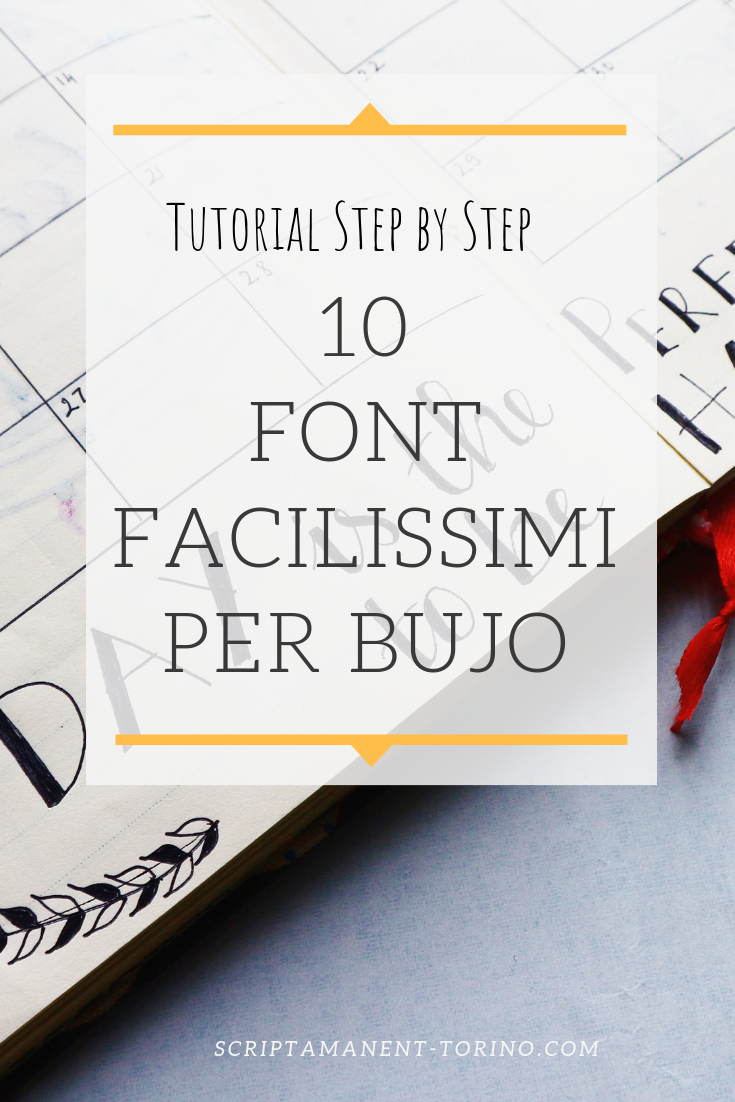
Font Scrittura A Mano Titoli
Fibre è un font moderno in stile scrittura a mano Tutti i caratteri sono di base diversi tra loro Le metriche e le creste di questo carattere in stile vintage sono state sviluppate per una certa facilità di lettura che solo un font interamente in maiuscolo può offrire HUMBLLE ROUGHT.
Font scrittura a mano titoli. Handwritten Font Bundle by Ian Barnard Ottieni un aspetto in stile “scrittura a mano” con questi font essenziali In questo fantastico pacchetto sono inclusi cinque font Bloomsbury Un carattere disegnato a mano in tre stili, Script, San e Serif, realizzati in modo da poterli utilizzare in combinazione tra loro. 10apr Esplora la bacheca "Calligrafia titoli" di Antonella su Visualizza altre idee su font di scrittura, idee per diario, scrittura a mano. 30giu Esplora la bacheca "Scritte per titoli e appunti" di Azzurra Genovese su Visualizza altre idee su scrittura a mano, font di scrittura, alfabeto scritto a mano.
Un font corsivo scritto a mano di solito non è davvero scritto a mano, è solo progettato per apparire come esso è Font in questo stile includono scolastico, Snell Roundhand e Santa Fe Molti font con la parola "script" nei loro nomi sono i caratteri della scrittura a mano di ispirazione corsivo, come Edwardian Script, Script e Bickham Brush. Tutte le 100% gratuiti base Sans Serif Serif Slab Serif manoscritto decorativo Dingbats non latino Pixel stile 3D squadrato cartoni carino arricciato futuristico Grunge bordo a mano pennellato corsivo calligrafia graffiti scrittura a mano schizzato graffiato stencil storico art deco art nouveau scrittura gotica medievale Retro macchina. L'app Font Changer ha la più grande raccolta di caratteri sul Play Store Crea i tuoi messaggi più interessanti, aggiornamenti di Facebook, Instagram Bio o tweet con oltre 110 caratteri speciali!.
26mar Esplora la bacheca "Scritture" di Sofia Mary su Visualizza altre idee su Scrittura a mano, Scrittura, Calligrafia. Imitano la scrittura a mano e anche questi sono font perfetti per un sito professionale, almeno per i titoli, perché conferiscono eleganza e stile alla pagina Un esempio di utilizzo di un font calligrafico Font gotici. Tutte le 100% gratuiti base Sans Serif Serif Slab Serif manoscritto decorativo Dingbats non latino Pixel stile 3D squadrato cartoni carino arricciato futuristico Grunge bordo a mano pennellato corsivo calligrafia graffiti scrittura a mano schizzato graffiato stencil storico art deco art nouveau scrittura gotica medievale Retro macchina.
7apr Esplora la bacheca "lettering" di Elisa Vanzani su Visualizza altre idee su Idee per diario, Font di scrittura, Idee per appuntamenti. Sono originali e intramontabili i font calligrafici sono perfetti per i tuoi progetti grafici, specialmente se hai l’esigenza di una tipografia sofisticata o ricercata Sul web sono disponibili centinaia di font, free e non in questo articolo ho voluto selezionare per te i 25 font calligrafici che reputo migliori e capaci di dare ai tuoi lavori quel tocco che può fare la differenza. Font di Scrittura a Mano La scrittura a mano può essere un concetto molto distante per tante persone nell’odierno mondo digitalizzato, grazie ai vari dispositivi elettronici, e non è strano che nella maggior parte dei casi incontriamo i noiosi Times New Roman o Verdana, anche se riceviamo un biglietto d’auguri.
Progettato prendendo ispirazione dalle insegne delle lavanderie di San Francisco, questo font è perfetto per i titoli e per tutti quei progetti in cui si vuol ottenere un effetto vintage DOWNLOAD 5 Monthoers è un font che simula le caratteristiche delle lettere stampate a mano. Imitano la scrittura a mano e anche questi sono font perfetti per un sito professionale, almeno per i titoli, perché conferiscono eleganza e stile alla pagina Un esempio di utilizzo di un font calligrafico Font gotici. Tutte le 100% gratuiti base Sans Serif Serif Slab Serif manoscritto decorativo Dingbats non latino Pixel stile 3D squadrato cartoni carino arricciato futuristico Grunge bordo a mano pennellato corsivo calligrafia graffiti scrittura a mano schizzato graffiato stencil storico art deco art nouveau scrittura gotica medievale Retro macchina.
10apr Esplora la bacheca "Calligrafia titoli" di Antonella su Visualizza altre idee su font di scrittura, idee per diario, scrittura a mano. I migliori convertitori di testo per convertire testo noioso in testo divertente!. Un generatore di font e uno switcher di s crittura per il copia e incolla diretto Converte il testo in testo semplice in vari stili di font come i font per tatuaggi, i font per la scrittura a mano, i font per script web, i font corsivi, i font scritti a mano, i vecchi font inglesi, le lettere, i bellissimi font o i font artistici.
Caratteri dei quali con accenti con il simbolo dell'Euro. Il nostro obiettivo è quello di realizzare l’effetto scrittura a mano utilizzando il pennello dell’effetto Scrivi sopraIl parametro da animare sarà pertanto la posizione del pennello Posizioniamo il pennello immediatamente sotto la prima R di River Quindi regoliamo la dimensione del pennello in modo da coprire interamente col diametro lo spessore del carattere. Adriana à € di Kong Font scaricati (6874 ieri) Shareware 4 file dei caratteri Scarica Dona all'autore Hello di Graphix Line Studio scaricati (6336 ieri) 21 commenti Gratis per uso personale 2 file dei caratteri Scarica Dona all'autore.
21ott Esplora la bacheca "Calligrafia" di Angela Pezzoli su Visualizza altre idee su calligrafia, scrittura a mano, scrittura. Quindi il font, in tipografia e informatica, è un insieme di caratteri per la stampa (stampatello è la scrittura a mano che richiama, con le lettere staccate, il carattere usato per la stampa) e per la lettura a monitor (carattere digitale, font installabile sulle nostre macchine e utilizzabile per la composizione). 14ago Esplora la bacheca "font di scrittura" di Cristianaoguguanebo su Visualizza altre idee su Font di scrittura, Scrittura, Idee per diario.
Anche se non è scritto a mano, imita la scrittura corsiva che crea immediatamente associazioni mentali legate al tocco personale Quando Usare i Font Corsivi Abbiamo già accennato ad alcuni potenziali casi d’uso, ma prendiamoci un momento per esplorare ulteriormente quando e dove usare i caratteri corsivi sul vostro sito web. L'uso di un font personale per la scrittura a mano è particolarmente popolare negli scrapbooking, per trasformare etichette e didascalie in una presentazione chiara ma individuale Altri siti, come Fontifier, richiedono una piccola tariffa per un servizio simile, ma c'è ben poca differenza tra i caratteri stessi. ɪɴꜱᴛᴀɢʀᴀᴍ ꜱᴛᴏʀɪᴇꜱ Stato di.